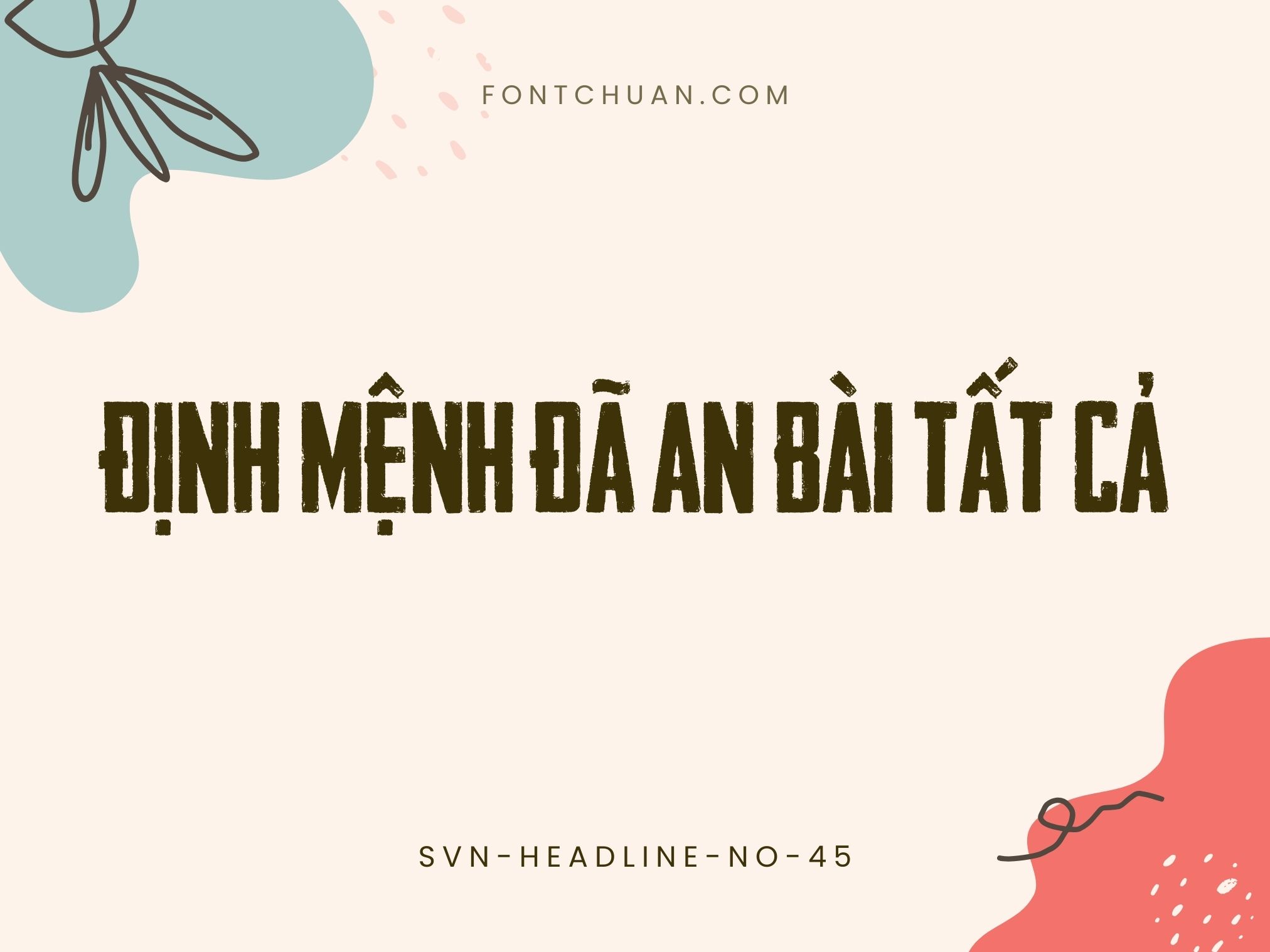
Font SVN Headliner No. 45 Việt Hóa
Tác giả Font: Kevin Christopher
Headliner No. 45 là một kiểu chữ sans-serif mang phong cách cổ điển mạnh mẽ, được thiết kế bởi Kevin Christopher và phát hành lần đầu bởi KC Fonts vào năm 2012. Font này đã được Việt hóa bởi Styleno.1 Fonts, hiện hỗ trợ đầy đủ tiếng Việt cùng hơn 100 ngôn ngữ khác trên toàn cầu. Thành viên của Font Chuẩn đã sưu tầm và lựa chọn kỹ lưỡng để phục vụ cộng đồng thiết kế với những yêu cầu khắt khe về tính thẩm mỹ và hiệu quả ứng dụng trong thực tế.
Với thiết kế dạng chữ in hoa, các đường nét đậm và hiệu ứng mài mòn đặc trưng, Headliner No. 45 mang đến cảm giác mạnh mẽ và dứt khoát. Font thể hiện tốt trên các tiêu đề, áp phích, bao bì sản phẩm và các thiết kế cần sự thu hút thị giác cao. Những lĩnh vực như quảng cáo, bất động sản, giáo dục và công nghệ đều có thể ứng dụng font này để tạo ấn tượng thị giác rõ ràng và chuyên nghiệp.